전시용 프리젠테이션 보드 - 폰트 사이즈
프레젠테이션 보드를 만들 때 우리는 특정 이미지를 어디에 배치하는지,
어떤 렌더링을 배치하는지 또는 어떤 글꼴과 글꼴 크기를 사용해야 하는지를 이해해야 합니다.
글꼴 크기는 전적으로 보드 크기에 따라 다르지만 일반적으로 사용해야 하는 글꼴 크기 범위는 다음과 같습니다.
기본 제목 글꼴 크기 / Main Title font size
이름에서 모든 것을 알 수 있으며, 기본 제목 은 일반적으로 프레젠테이션 보드의 내용이며 일반적으로 기본 제목은 하나뿐입니다. 보드의 레이아웃과 글꼴에 따라 이러한 글꼴 크기 중에서 선택할 수 있습니다.
제목 글꼴 크기 / Heading font size
분명히 모든 것에 항상 기본 제목을 사용하지는 않을 것입니다. 프레젠테이션 보드의 각 섹션에 제목을 지정하려면 제목이 있어야 합니다. 다른 글꼴로 제목을 강조 표시하거나 글꼴 크기를 조정할 수 있습니다.
본문 글꼴 크기 / Body font size
우리의 프리젠테이션 보드에는 일반적으로 그렇게 많은 텍스트가 없지만 소개, 프로젝트에 대한 간단한 설명 또는 특정 스케치, 그래픽 또는 렌더링만 설명하기 위해 텍스트가 있습니다. 그러나 이 글꼴 크기가 프레젠테이션 보드에서 중요한 섹션이 아니라는 것을 의미하지는 않습니다.
글꼴 조합
예, 올바른 글꼴 크기를 얻었습니다. 하지만 올바른 글꼴은 어떻습니까? 괜찮아요! 우리는 언제나처럼 여러분을 지원합니다. 다음은 프리젠테이션 보드에서 사용할 수 있는 몇 가지 글꼴 조합이므로 항상 같은 글꼴을 사용하지 않아도 됩니다. 프레젠테이션 게시판의 머리글과 본문에 번갈아 사용할 수 있는 다양한 글꼴을 살펴보세요.
1. 헬베티카 볼드 + 에브리마 / Helvetica Bold + Ebrima
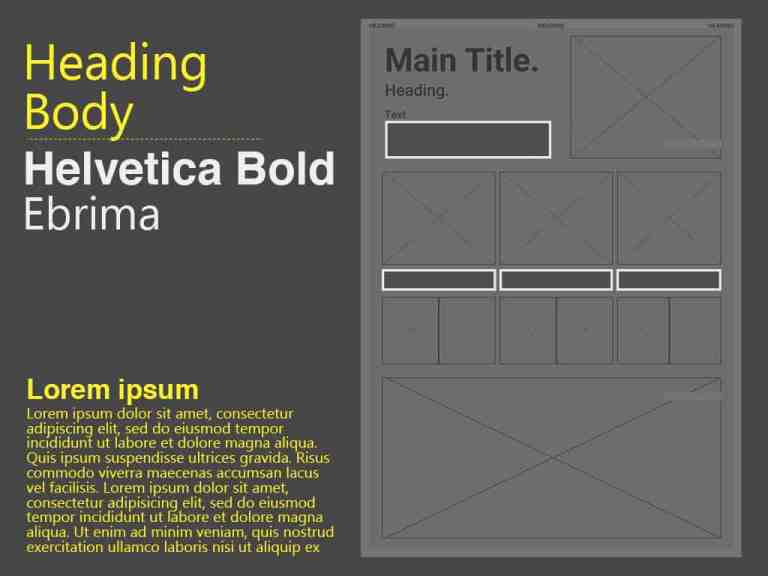
2. 라토 블랙 + 라토 레귤러 / Lato Black + Lato Regular
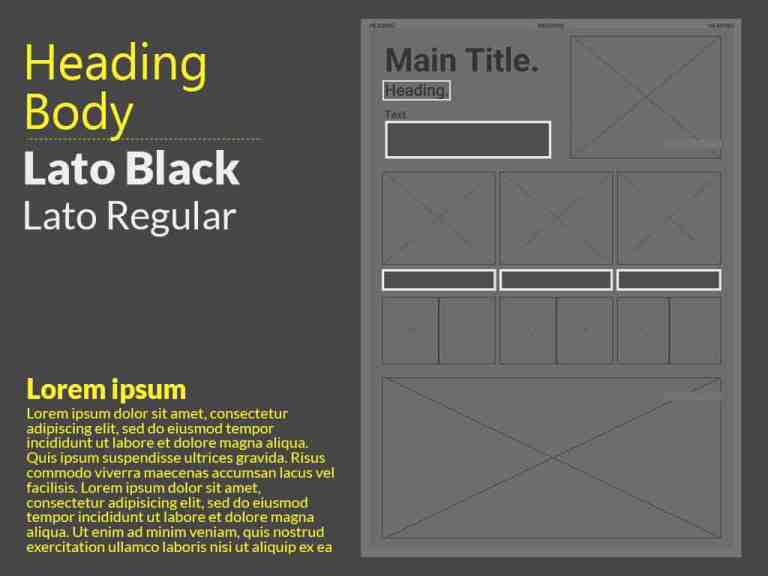
3. 오스왈드 볼드 + 몬세라트 라이트 / Oswald Bold + Montserrat Light
4. 가라몬드 + 헬베티카 노이에 / Garamond + Helvetica Neue
5. 로보토 블랙 + 누니토 라이트 / Roboto Black + Nunito Light